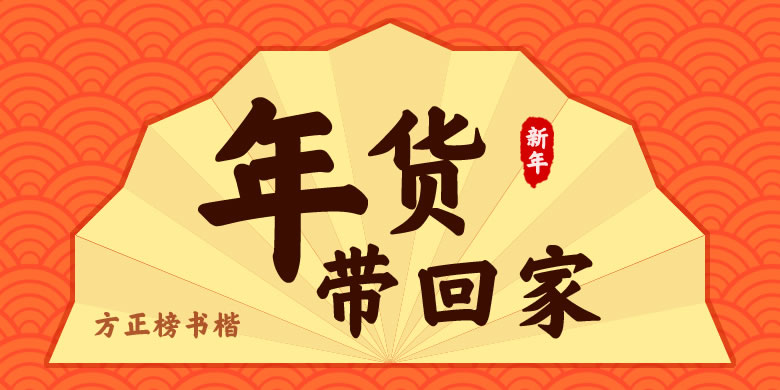
品牌:方正字库设计师:汪文发行时间:2014字库编码:大陆简体(GB2312-80)、大陆繁体(GB12345-90)、简繁扩展(GBK)分类:楷体
方正榜书楷的设计源于明、清两朝宫阙匾额、楹联上的楷书大字。榜书为历代书家所推崇。古人形容榜书:笔墨雍容,气韵中正,雄健磅礴,自古为难。古代宫阙榜书写者有皇帝、大臣等,风格各异,多为繁体和异体字。方正榜书楷在保持原书风貌的前提下设计了统一规整的简体字。其字形厚重疏朗、雍容大气,赋有艺术感染力,适用于具有传统习俗的包装和宣传设计,比如年历、年货等。